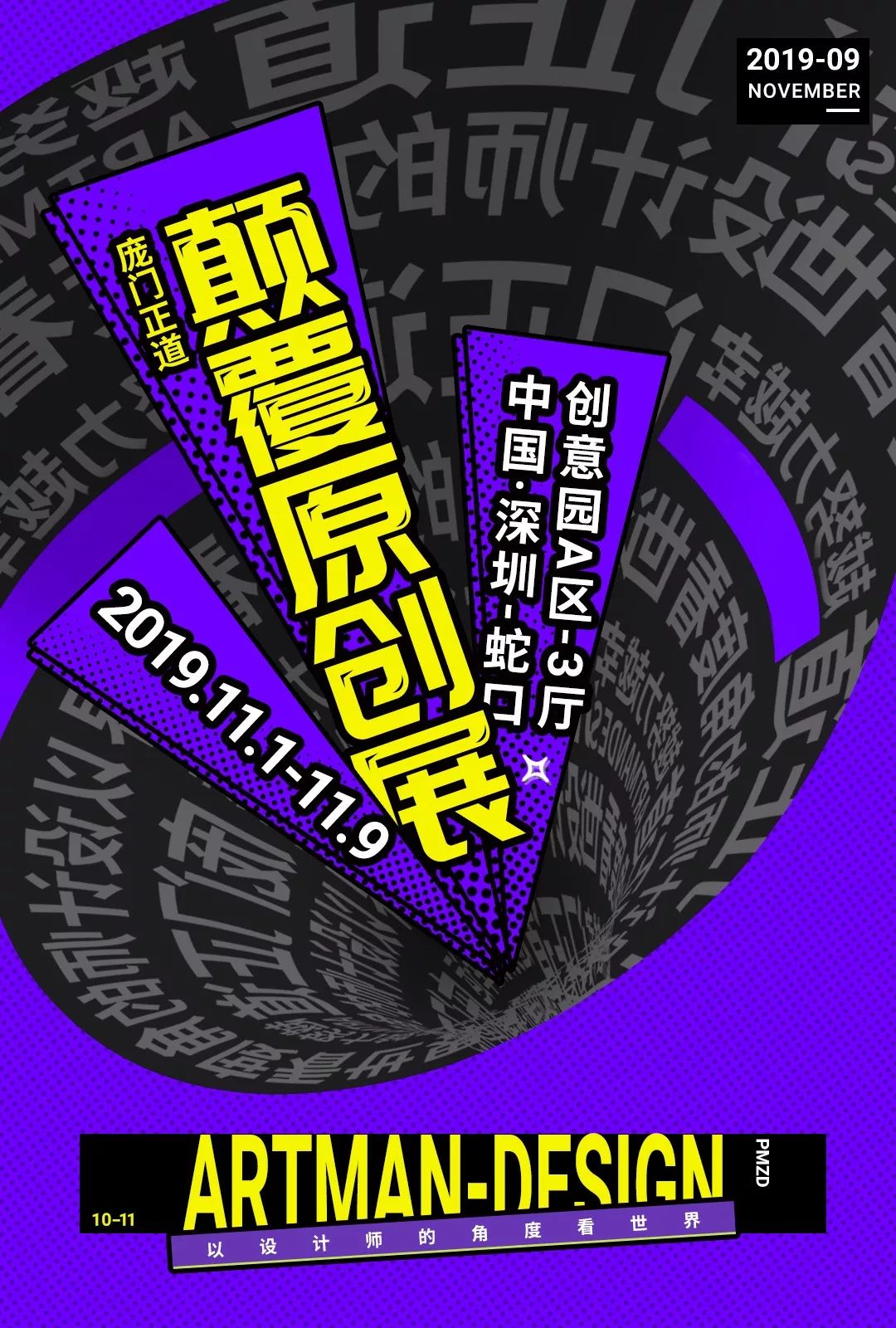
不用素材,用AI做扭曲文字,让文字绕起来!
新一期的AI 教程又来了!
之前教大家用 AI 做扭曲文字
来先立个flag
今天挑战不用素材
就做出空间感强的海报来
别不信先给你看成品
(太神奇了!)
哎真就没用到任何外部素材
怎么做到的呢?马上开始AI教程
打字:先在AI里打好要用的文字
复制字:把组好好的文字复制多个备用
新建符号:选中全部字执行CTRL+G对字进行编组,在打开窗口菜单下的符号,把编组后的字拖拽到弹出的符号框内,这时会弹出符号选项这时给新符号起个名字最后确定符号就新建好了。
画一条路径:选中钢笔工具勾勒一条路径
以上操作都很简单
注意看下面重点来了
3D饶转:选中路径,打开效果菜单下的3D-饶转,在弹出的3D饶转选项里勾选中预览,自:选中右边,最后调整到满意角度。
添加贴图:点开贴图,在弹出的贴图框里先勾选中三维模型不可见。在打开符号下拉菜单,找到刚刚新建的符号在调整缩放符号大小。最后文字3D绕转效果完成。
扩展外观:如果不进行扩展外观随意放大会让图形变形,这时打开对象-扩展外观这时随意放大缩小图形不会变形。
文字绕转效果就这么轻松愉快完成了
下面来做案例!!
这个海报用刚刚做好的3D绕转文字效果做海报的旋涡背景营造立体空间感颜色搭配黑色紫蓝色点缀黄色字让画面更有活力时尚感。
最后在看一遍高清大图